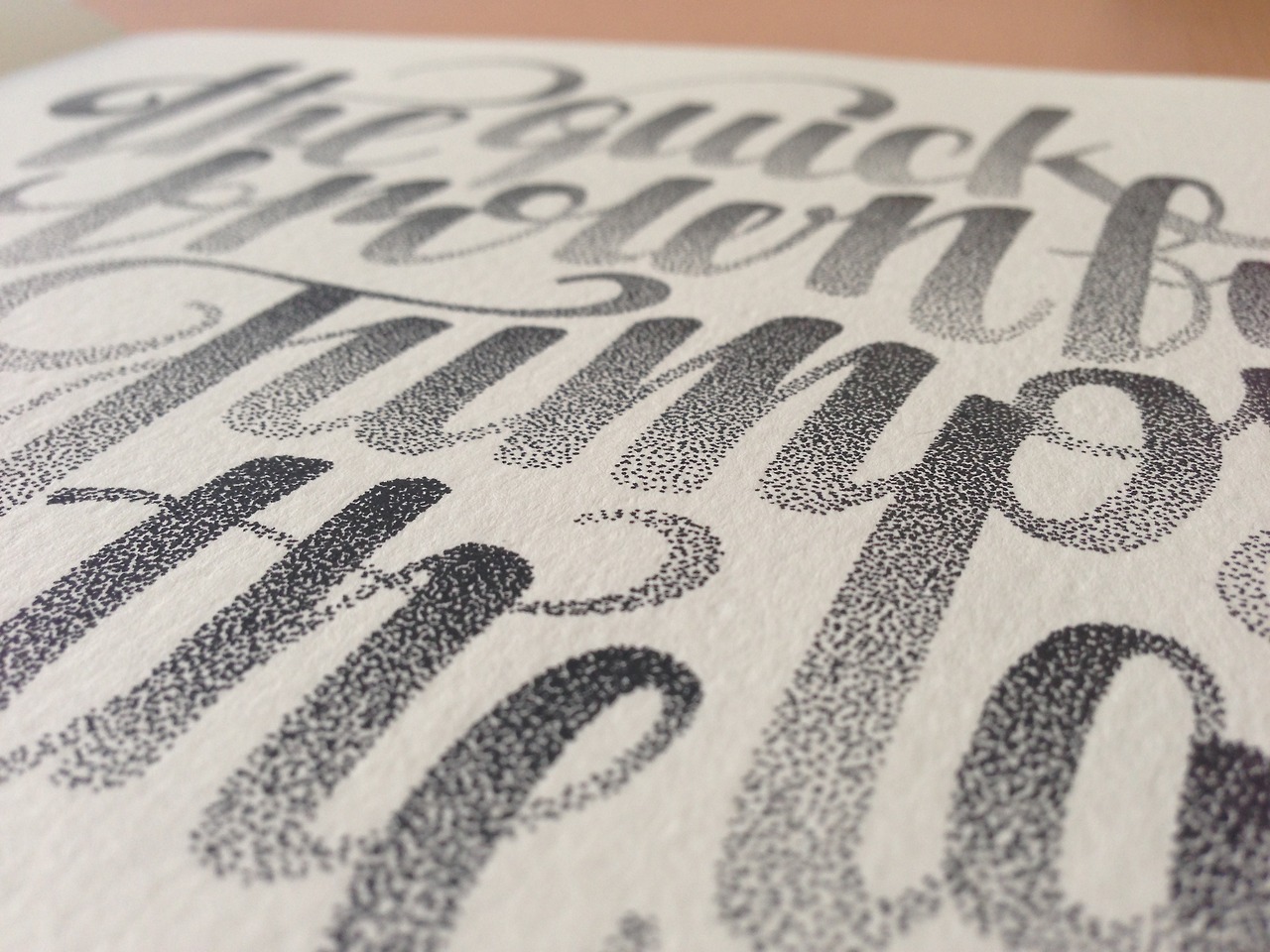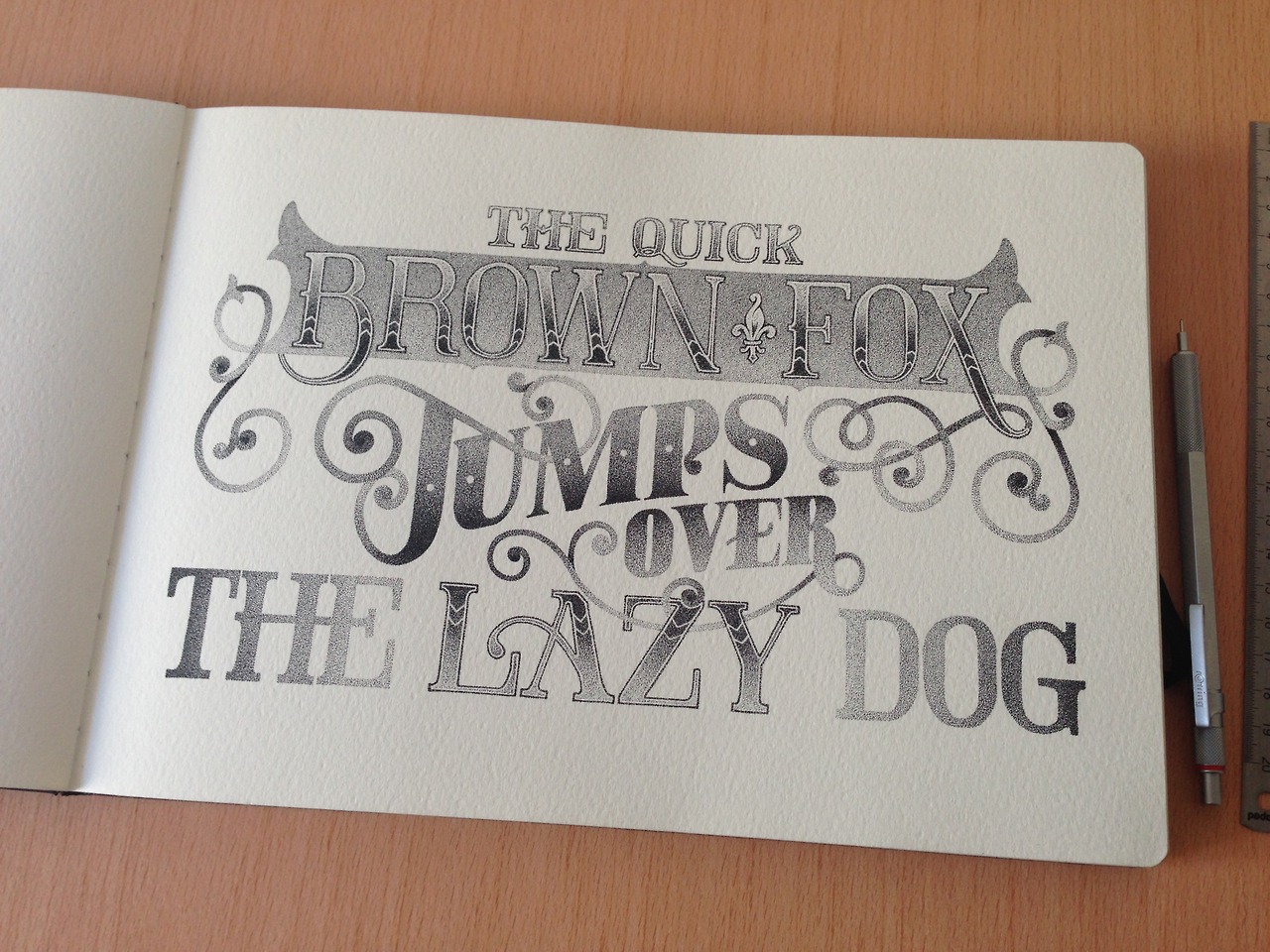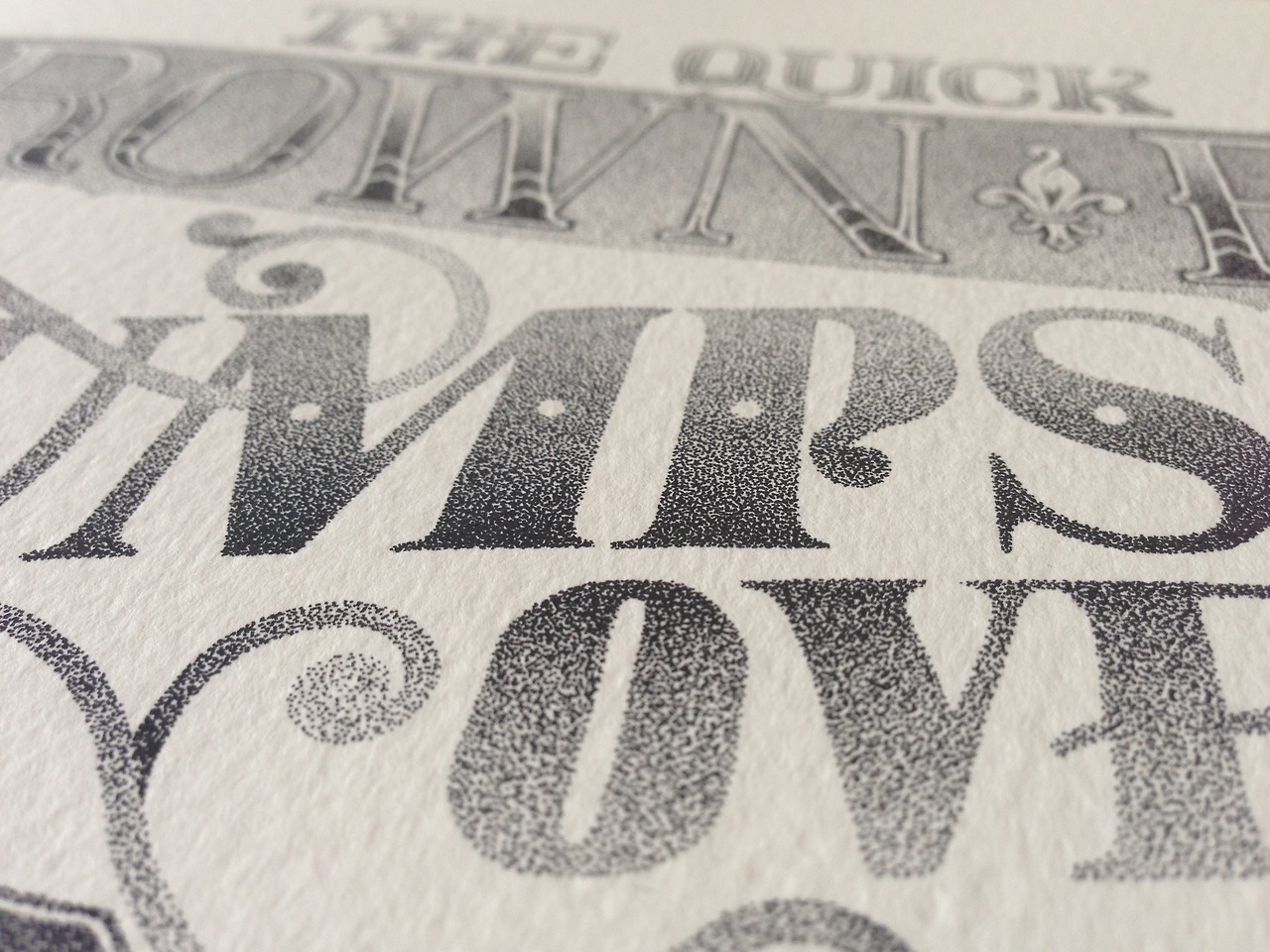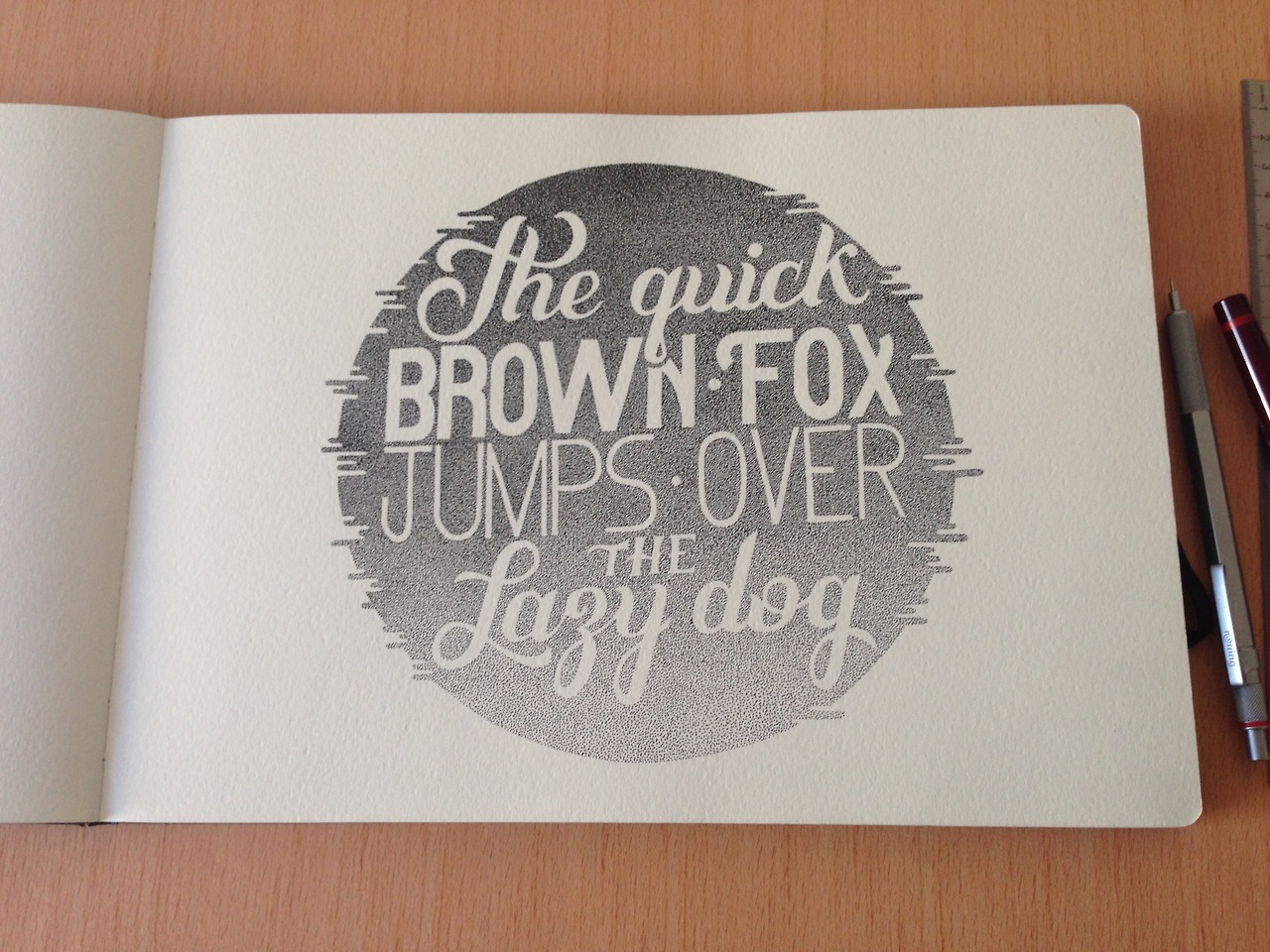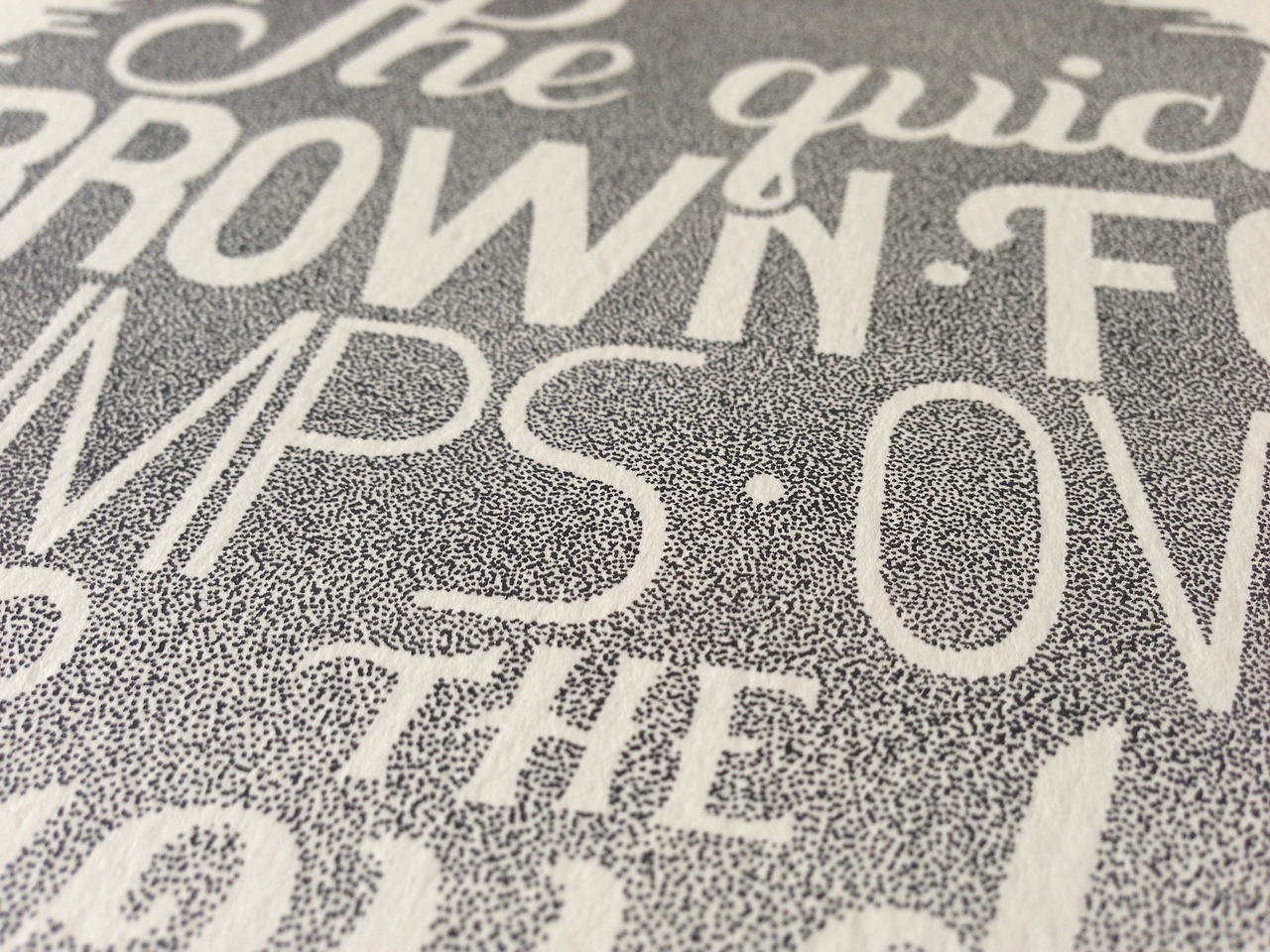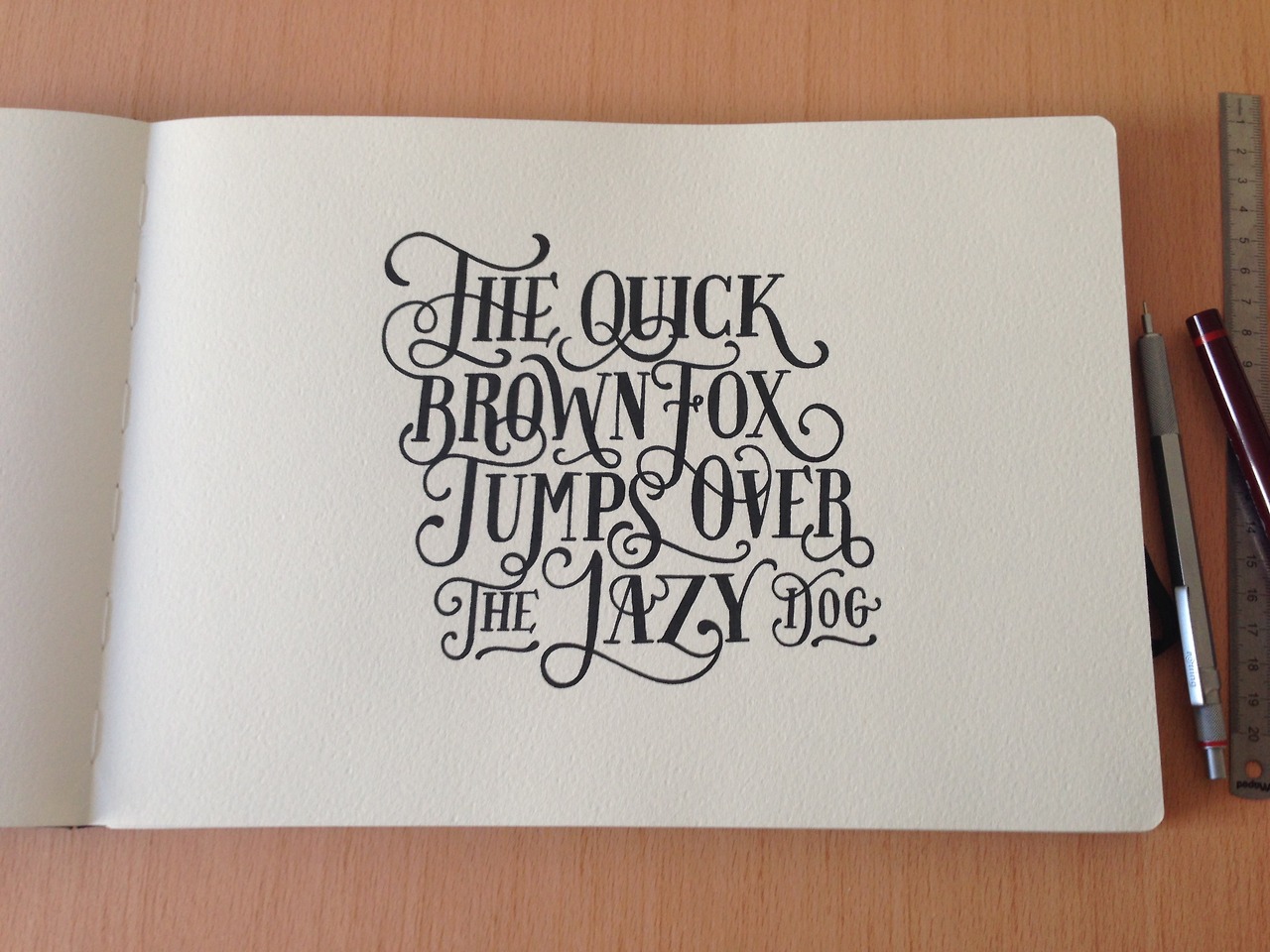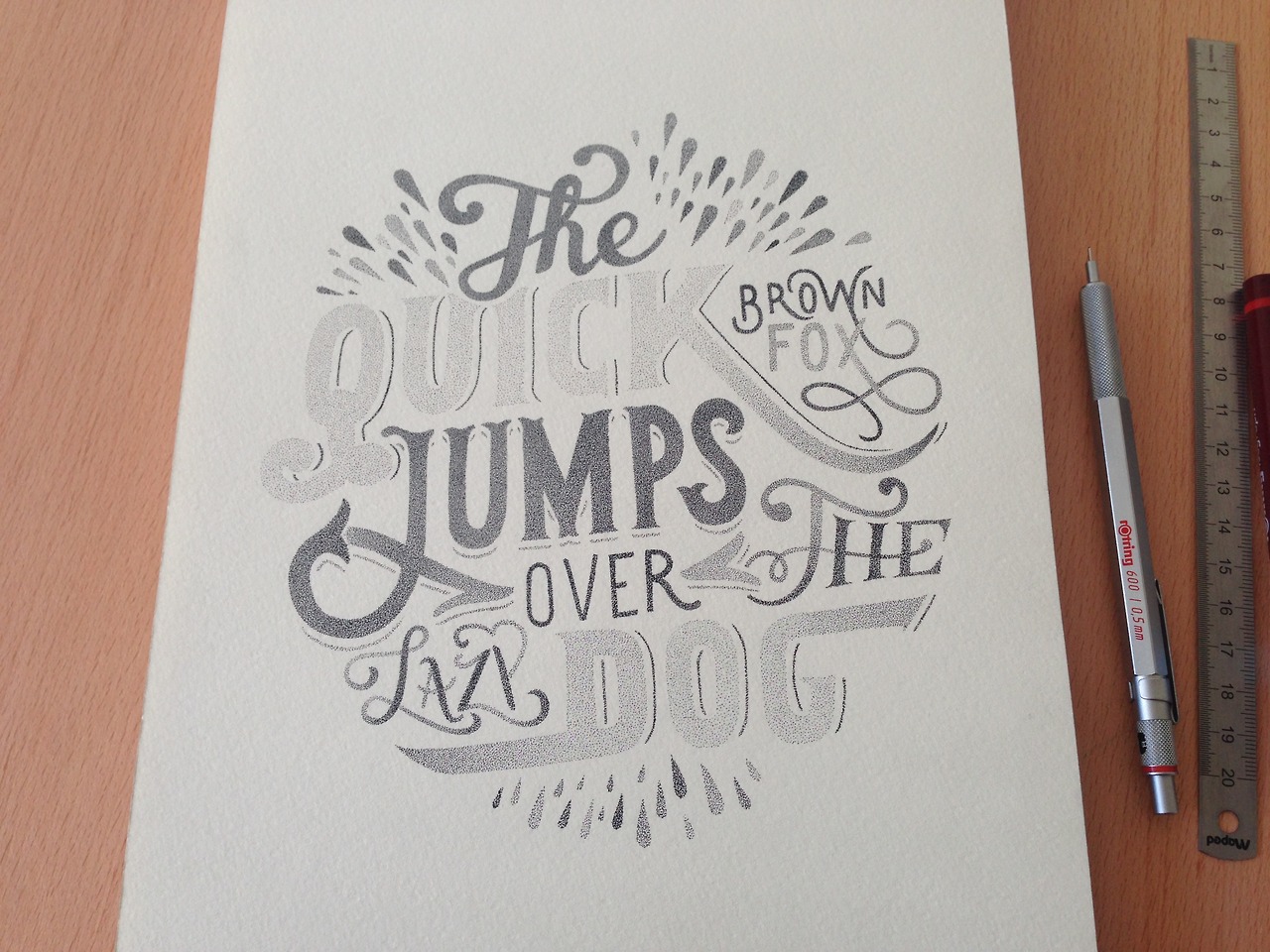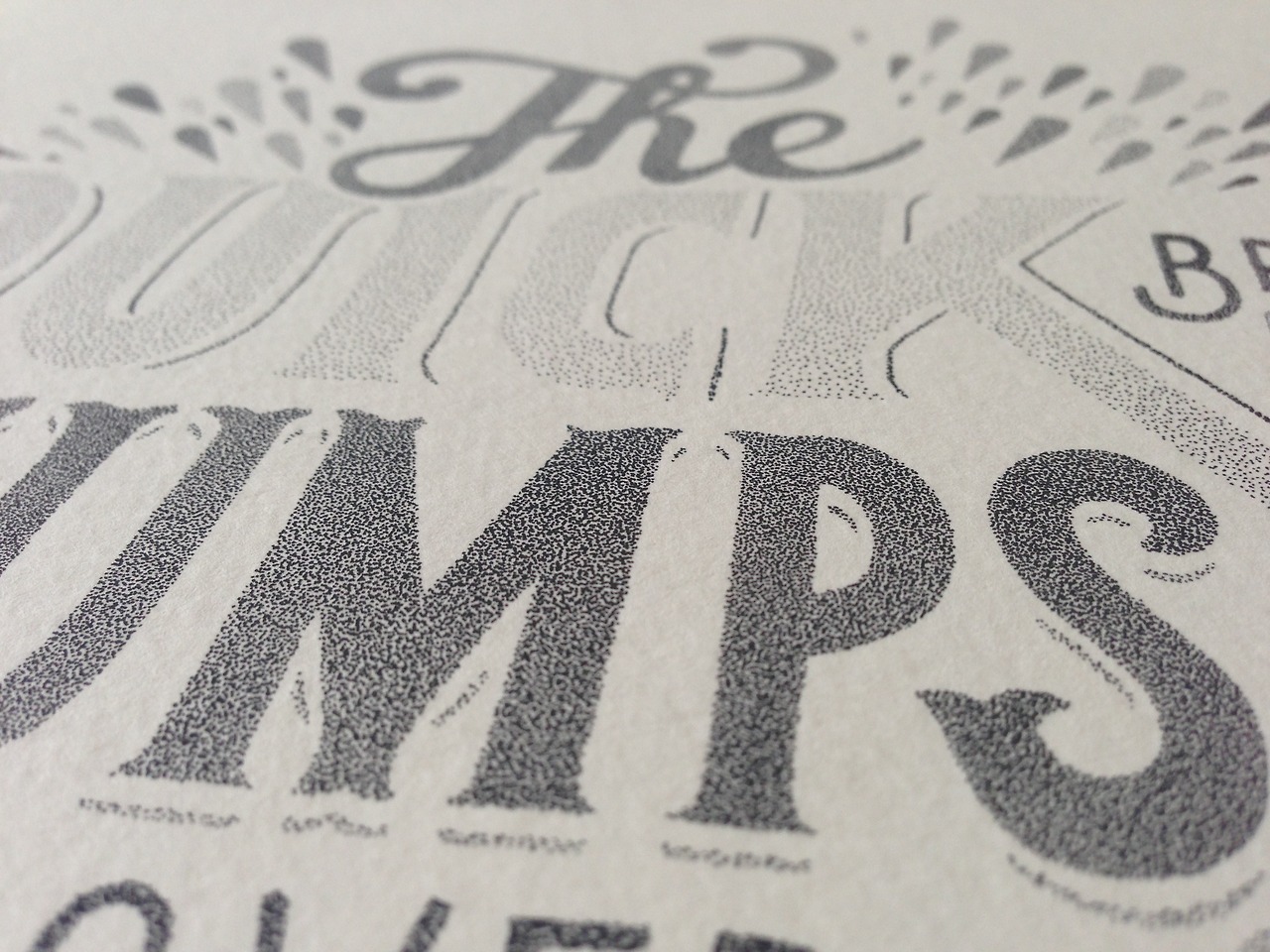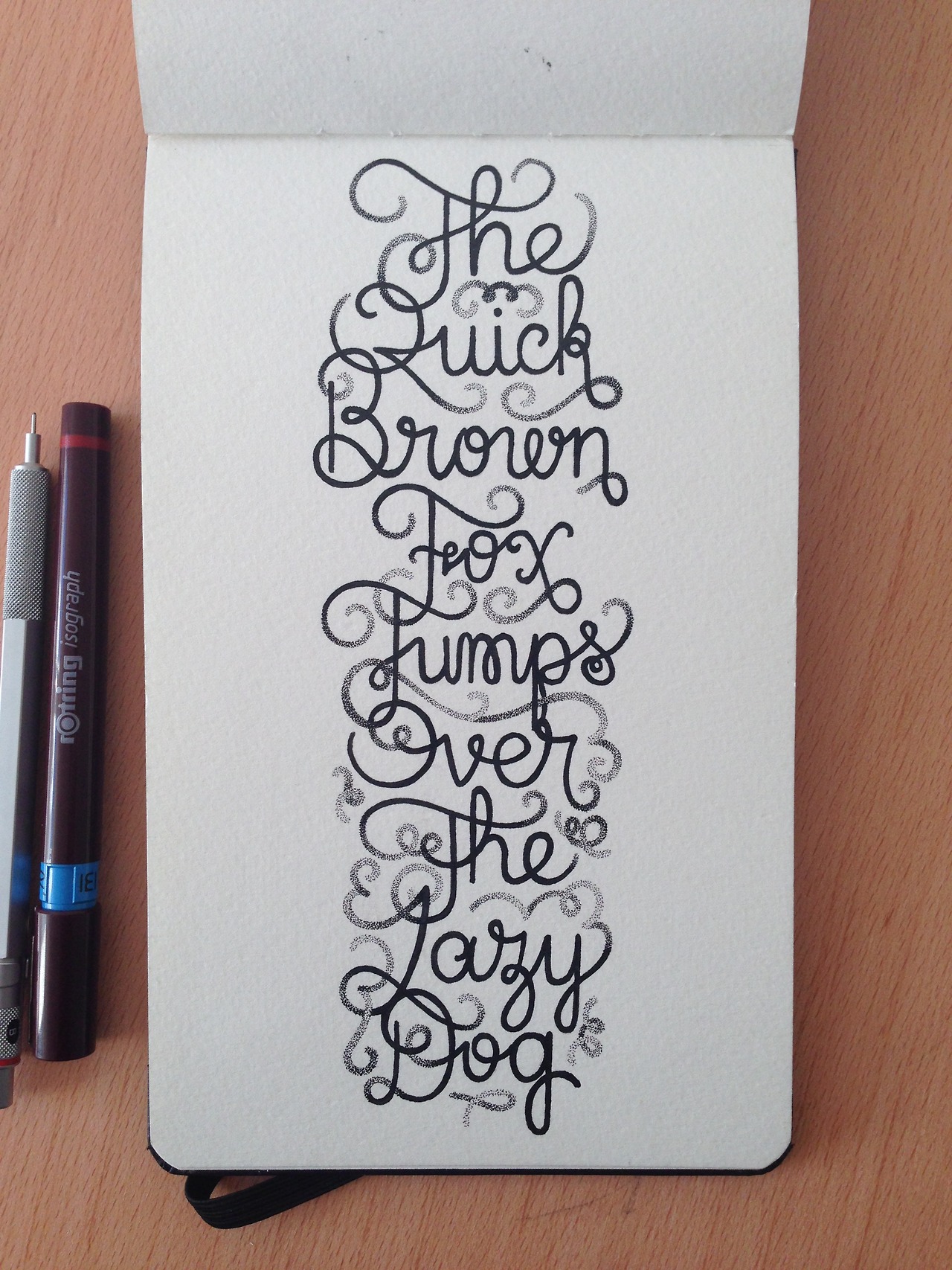
El ilustrador francés Xavier Casalta nos deja con la boca abierta al mostrarnos como con su lápiz negro Isograph 0.10mm y su técnica de miles “puntitos” crea formas tipográficas, sombras y degradados de una calidad espectacular. A través del proyecto “The quick brown fox jumps over the lazy dog” podéis ver un como se las gasta este joven artista.